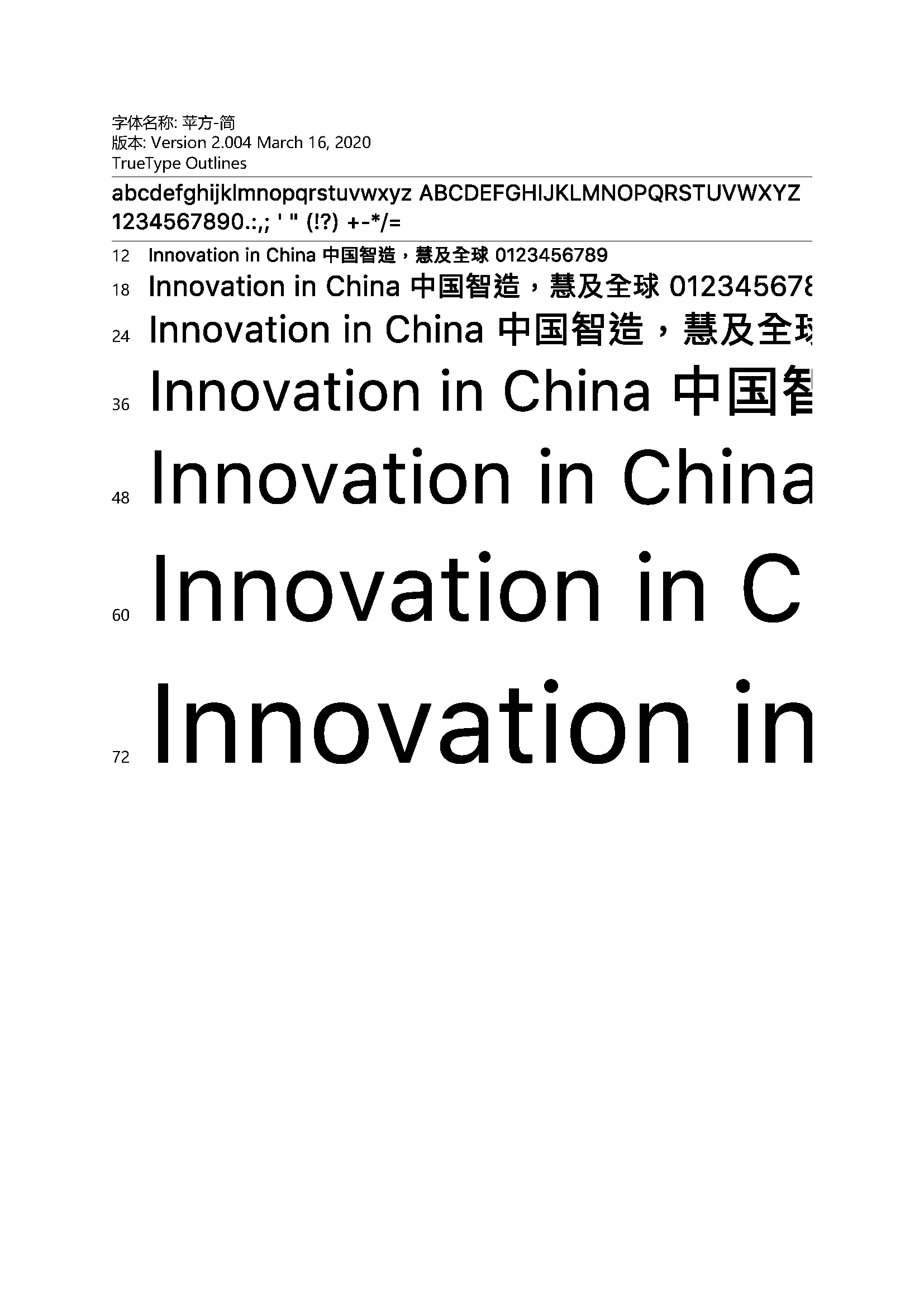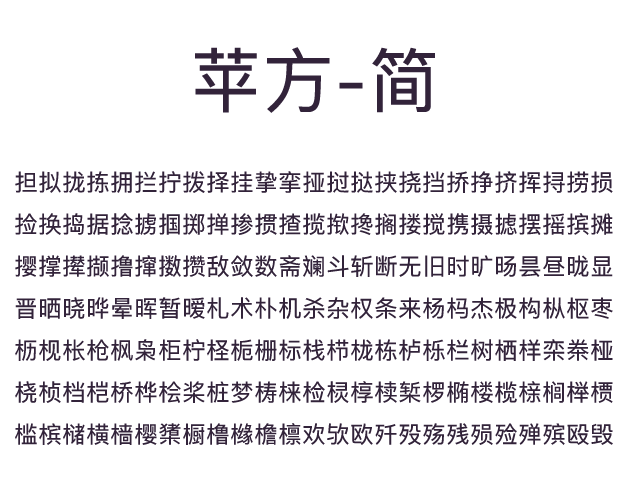
苹方-简.ttf 字体名称: 苹方-简 版本: Version 2.004 March 16, 2020 TrueType Outlines 新版本字体做了一些优化 苹方-简是由苹果设计的一款全新的中文系统字体,该字体支持苹果的动态字体调节技术,能够自动根据字号动态调整字间距以及字体高度,从而达到最佳的阅读效果,同时苹方简体字体不仅字型优美,而且能提升在手机、电脑屏幕上的清晰度以及易读性。 字体下载地址 点击去下载